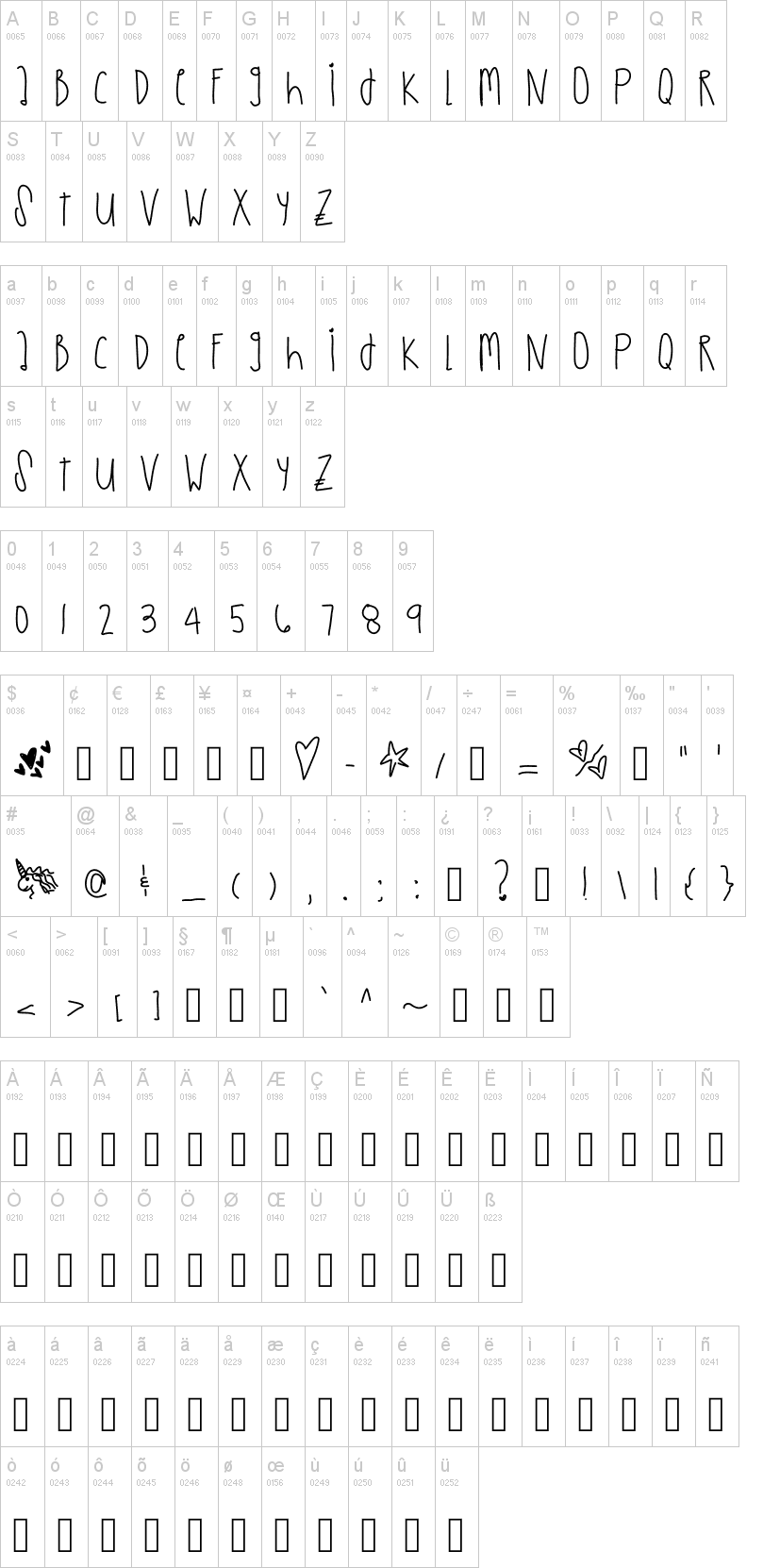
Paris Views
Paris Views 是一种优雅优美的手写风格字体,由设计师Sandy Luke设计。这种字体有一种独特的法国风情,适用于各种设计项目,如印刷品,包装,海报,标志等。它的流畅笔画和柔和线条使得它看起来非常优雅,同时也非常易于阅读。 Paris Views 字体有多种字重可供选择,使得它非常适合于各种设计需求。如果你正在寻找一种具有法国风情的优美字体,那么 Paris Views 绝对值得一试。
Paris Views是一款非常不错的手写艺术字体,具有很好的视觉感,适合于文化类的宣传设计、商业类品牌的广告和产品包装设计以及个性化文字排版等较多场景。
Paris Views字符映射图